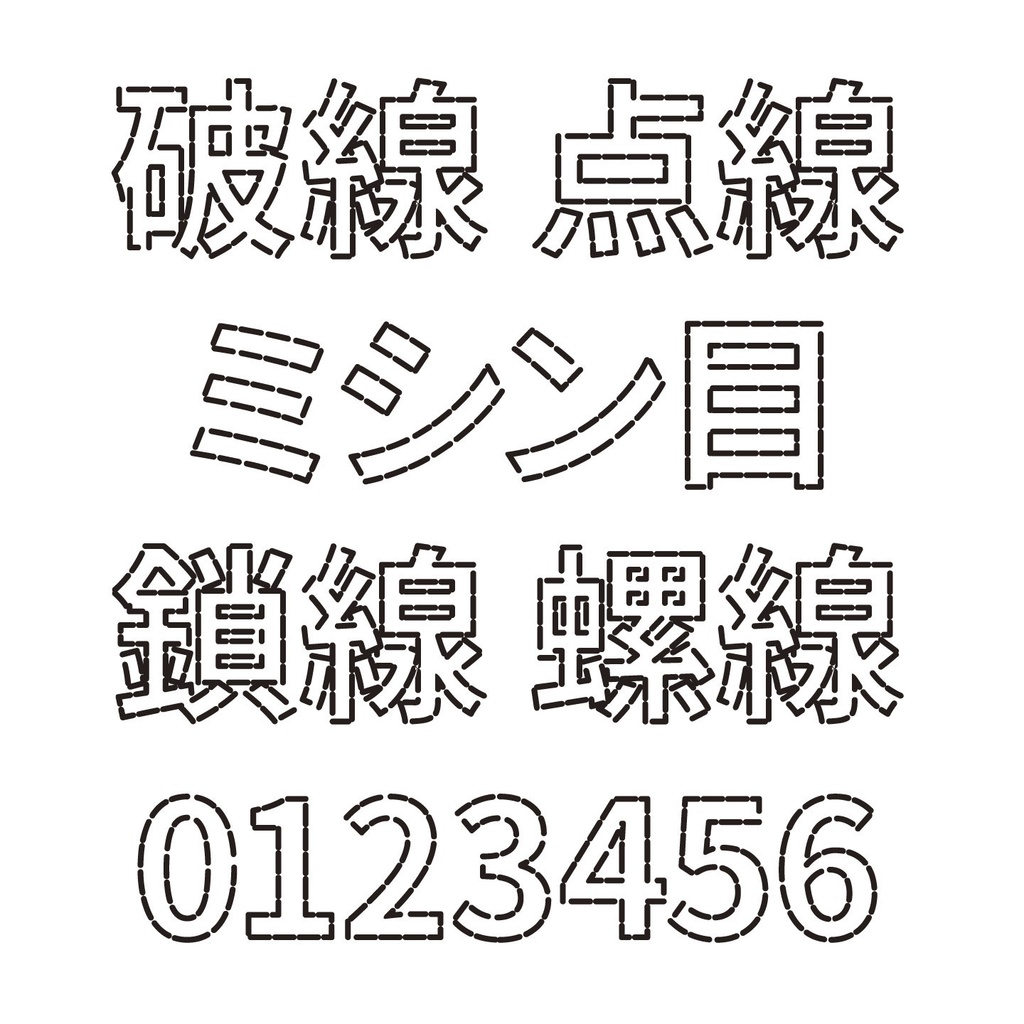
基于思源黑体改的虚线 GB黑体,免费商用字体
基于思源黑体改的虚线 GB黑体,可用于商业用途,适合大标题使用,不适合小字号。
虚线 G [免费版]
Source Han Gothic 字体已使用 Glyphs 软件中的过滤器进行处理,以创建穿孔边框。这是一种免费的日文字体,可用于标题。包括二级汉字在内,字符数约为8,200个。您可以免费将其用于个人用途或商业用途。